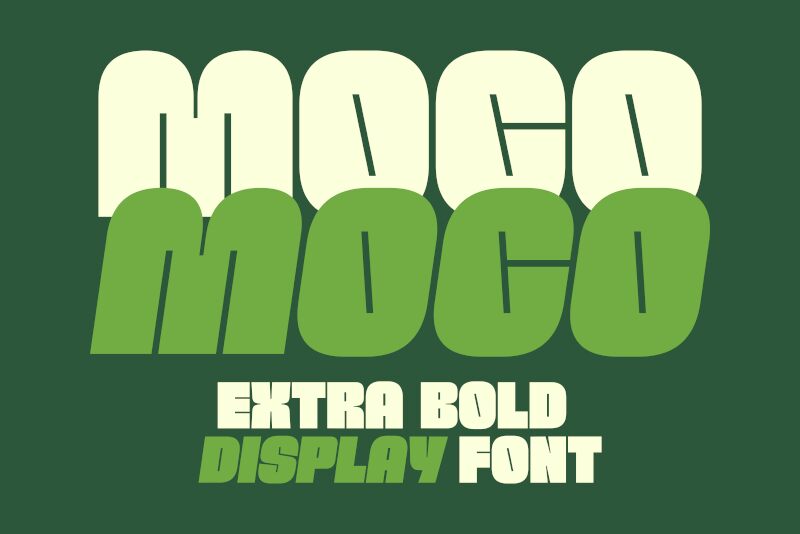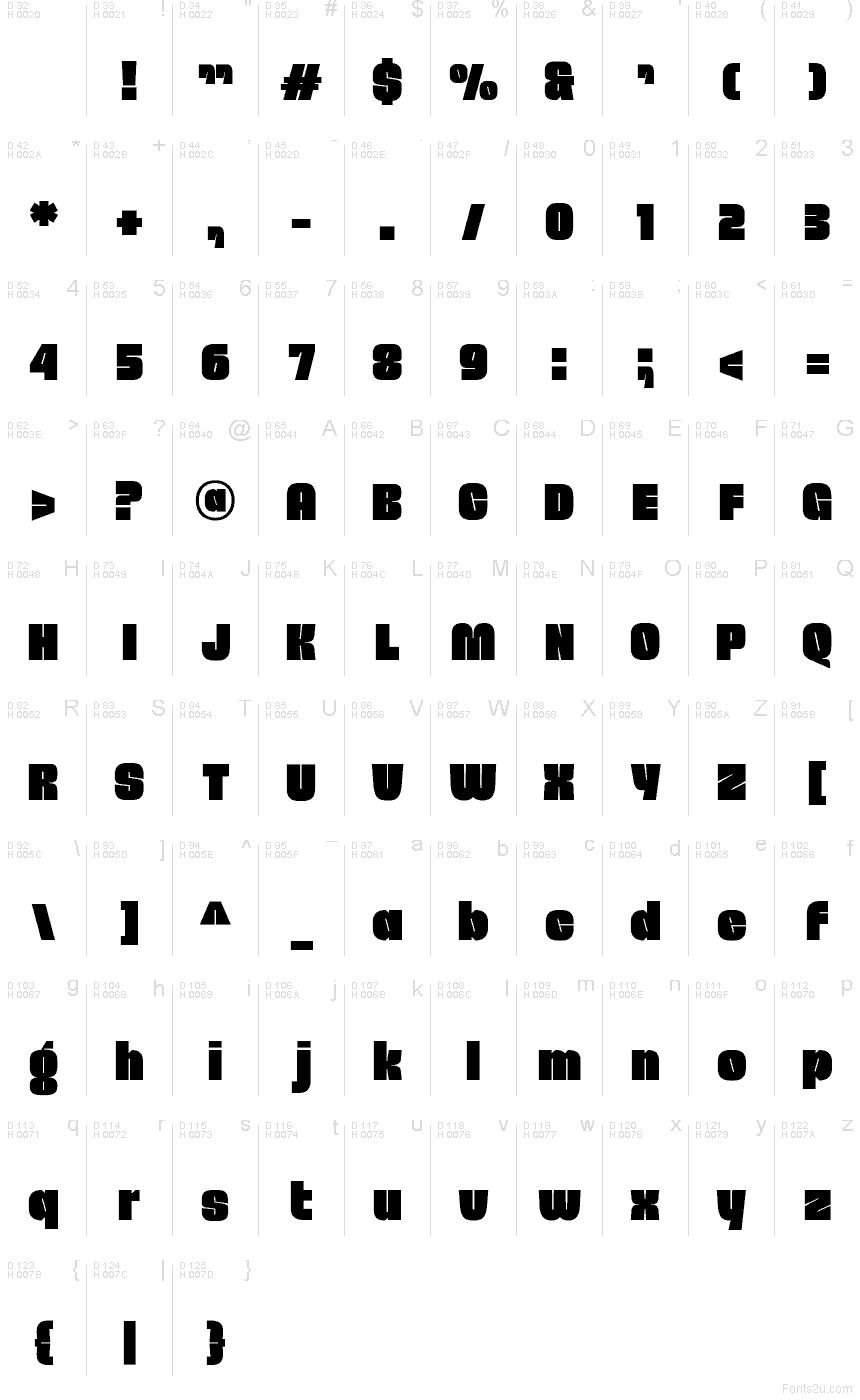
Moco od Glyphminds Studios je bezplatné, stylové titulkové písmo s masivními velkými písmeny v duchu 70. let a měkkou, nafouknutou siluetou. Písmena působí hutně a hravě, jsou postavena na velkých zaoblených tvarech s úzkými vnitřními řezy a pruhovými mezerami, které dodávají písmu plakátový rytmus, namísto abychom sklouzli k ohranému retro klišé.
Hodí se na hudební letáky, obaly, branding kaváren, festivalové plakáty a titulky, kde pár slov potřebuje odvážný, výrazný postoj. Jako bezplatné písmo funguje Moco Regular skvěle také pro titulní karty, monogramy a krátké logotypy, protože opakující se zaoblené tvary a štíhlé vnitřní mezery udržují písmena živá i v těsných, kompaktních sazbách.